ハロウィンフォントPack(6書体set)Halloweenにぴったり 期間限定
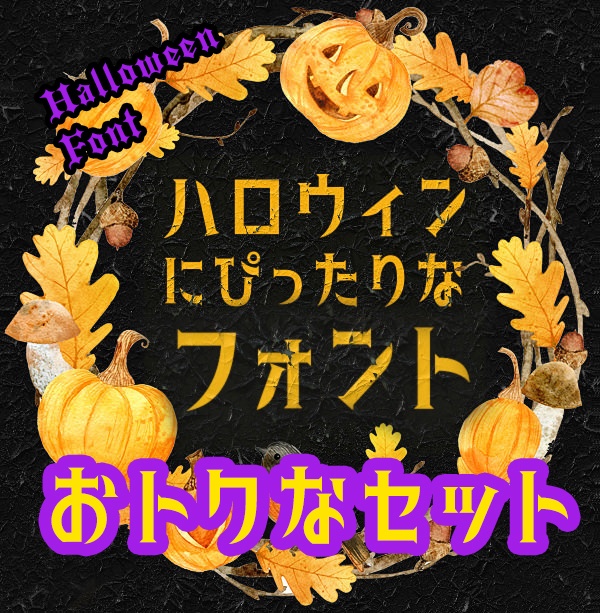
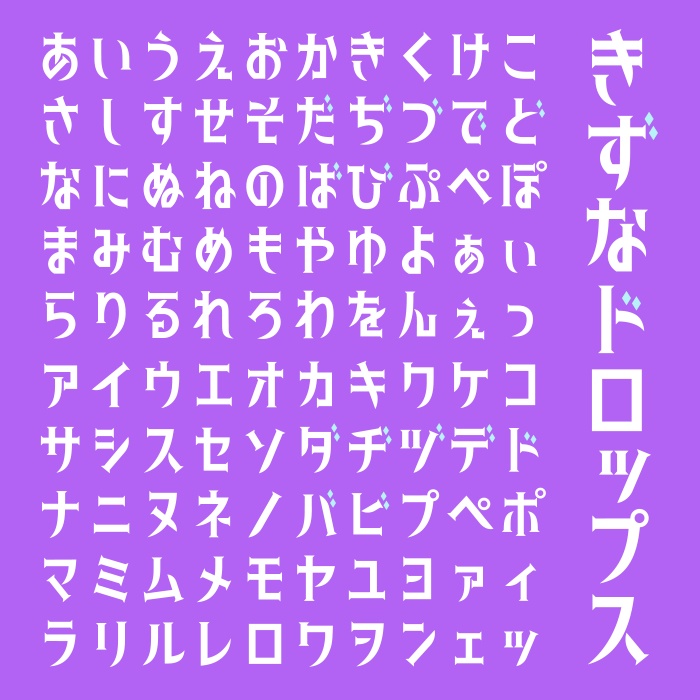
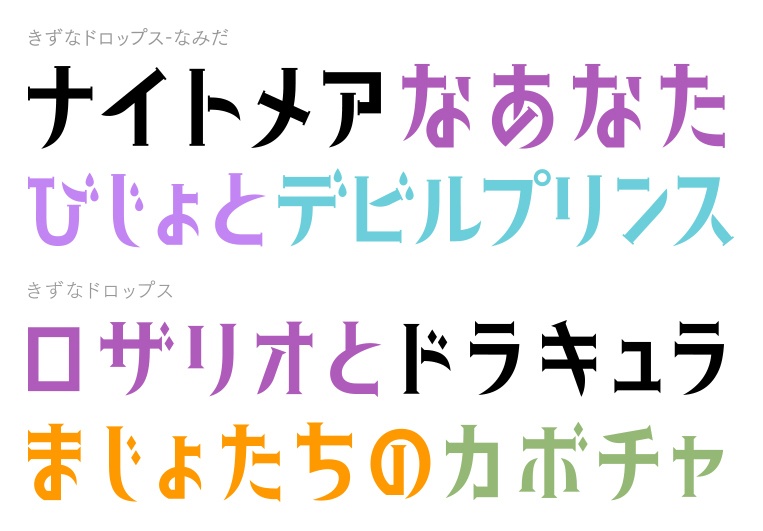
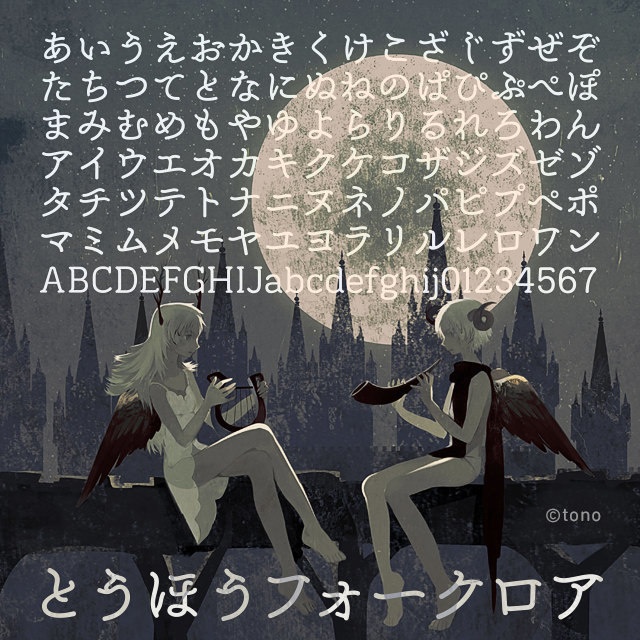
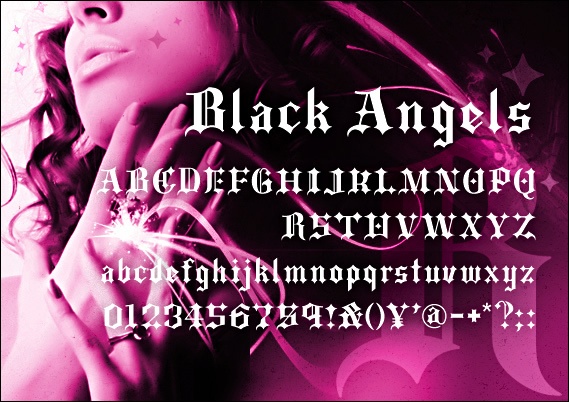
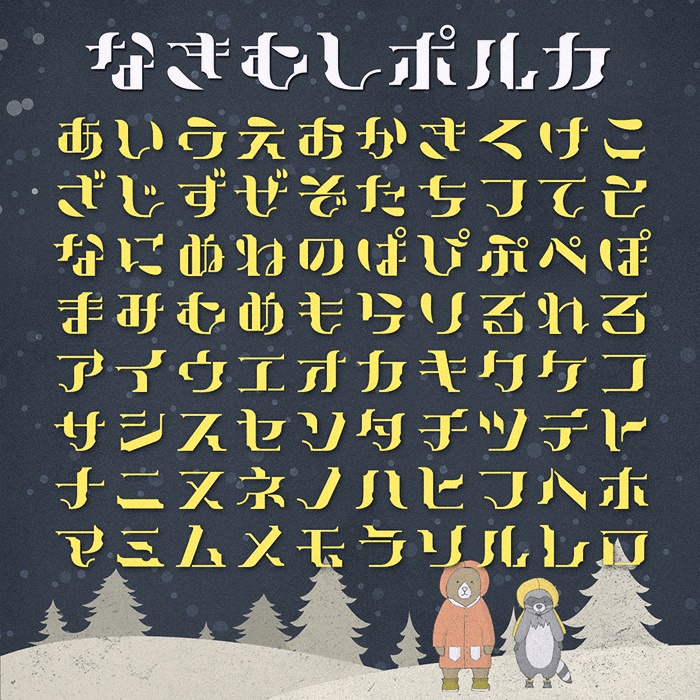
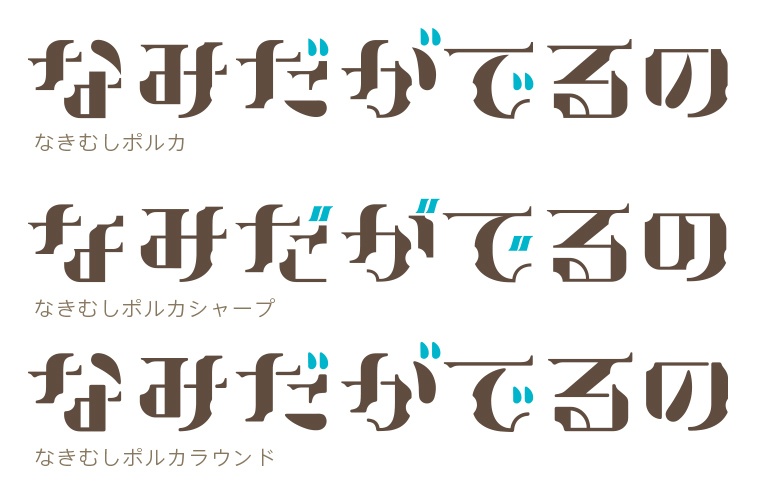
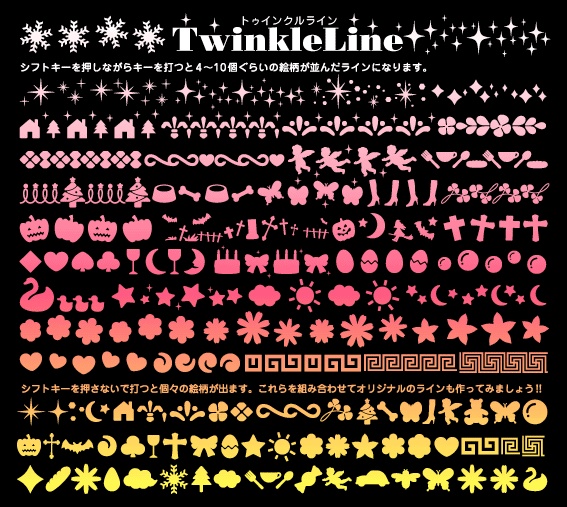
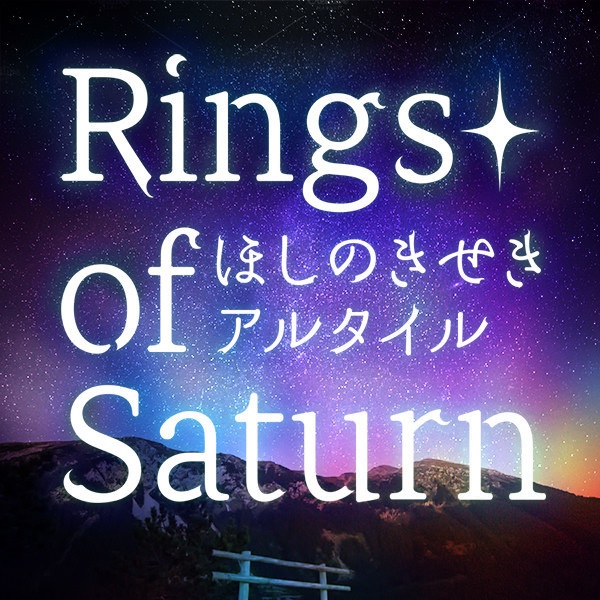
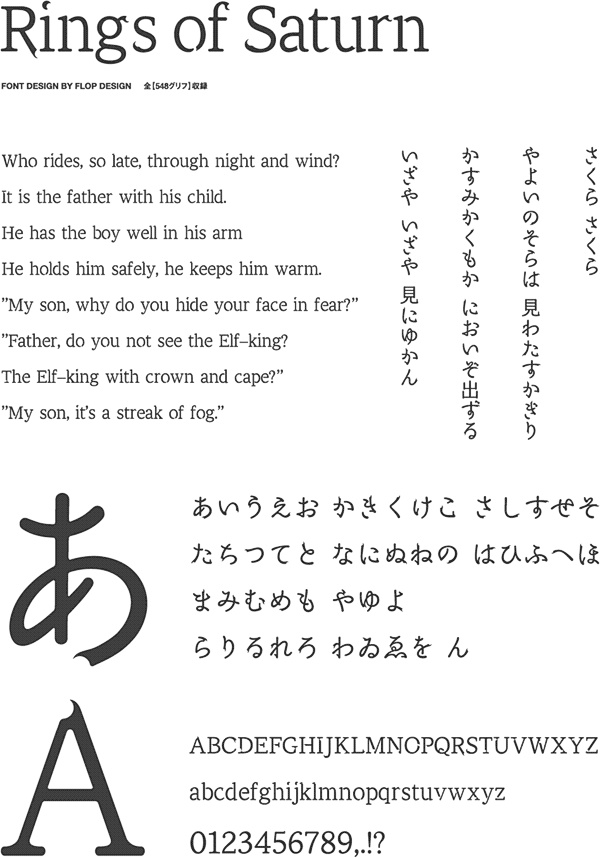
きずなドロップス(2フォントset)、とうほうフォークロア、Black Angels、なきむしポルカ(3フォントset)、Twinkle Line、Rings of saturn(オマケ)の6つの書体(9フォント)のセットです。 期間限定の販売になります。(おそらく10月半ばぐらい、さすがにハロウィンの準備も近くなりますので) ■動作環境 Mac:システム/OS X対応(10.x)〜最新のOS X Windows:OS/日本語版Windows2000、XP、VISTA、Windows7、Windows8、Windows10 フォント形式:OpenTypeフォントおよびTrueTypeフォント ■収録文字数について きずなドロップス、とうほうフォークロア、なきむしポルカは、ひらがな・カタカナのみのフォントになります。 Black Angelsはアルファベット・数字・記号のみのフォントになります。 TwinkleLineは絵文字のみのフォントになります。 Rings of saturnはひらがな・カタカナ・アルファベットのみのフォントになります。 ■安心して使えるロイヤリティフリーの書体 あらゆる商用・デザイン用途(印刷物・ゲーム・アプリ・映像・動画・ロゴ・同人作品)に使用できる、商用申請の必要のないロイヤリティフリーの書体になります。文字の加工・変形も可能です。ご安心ください。